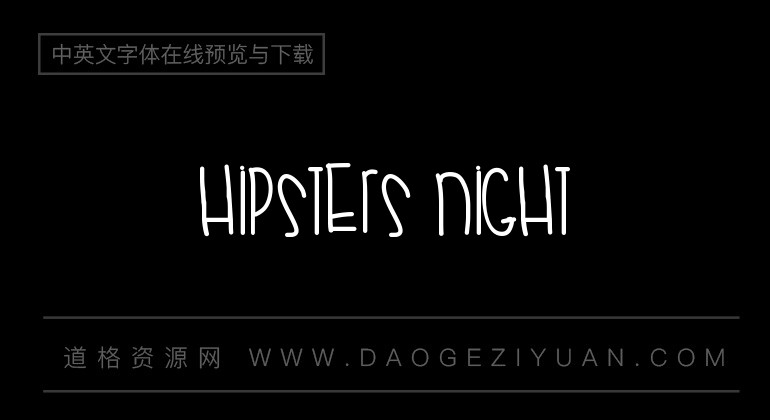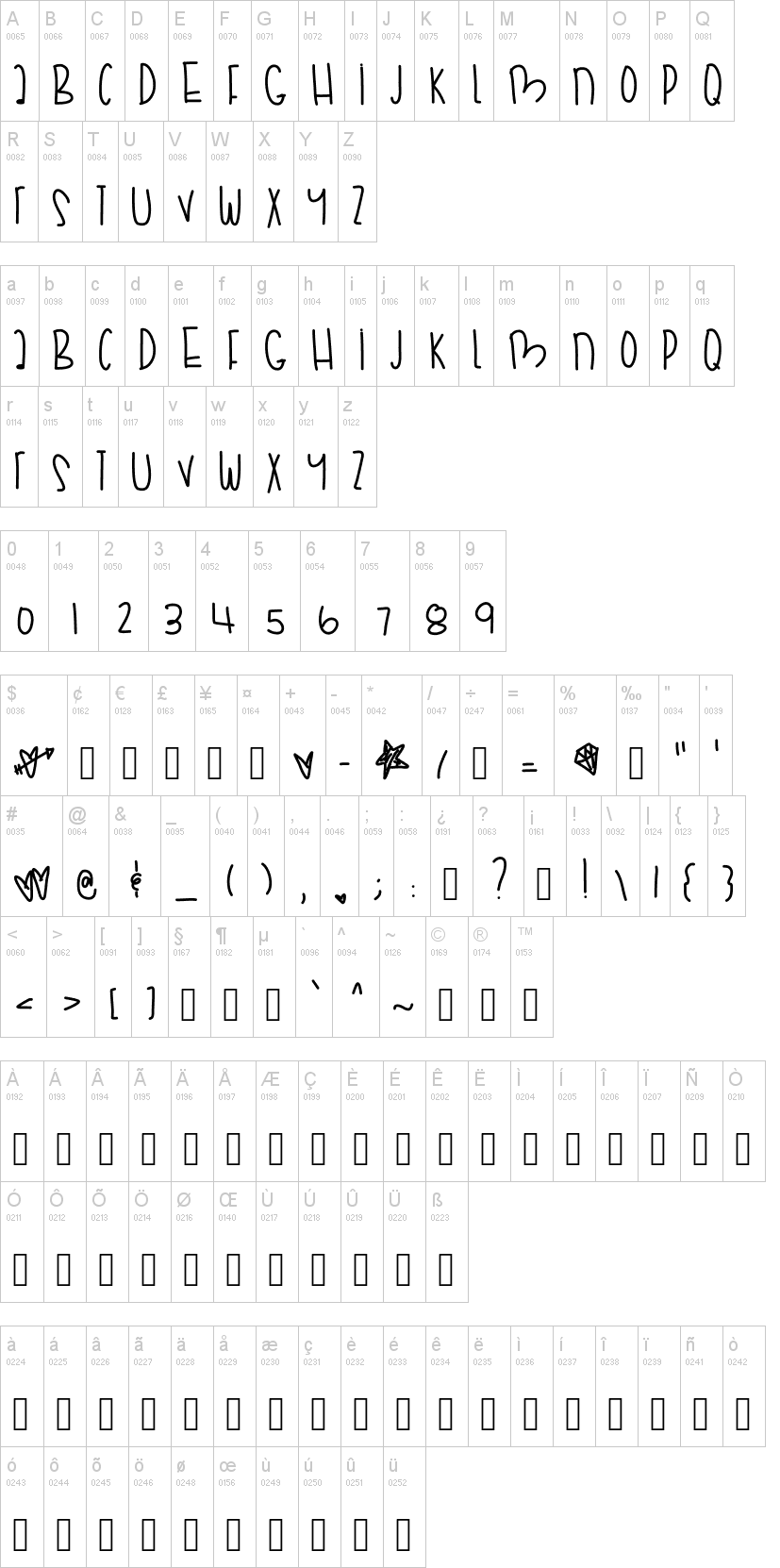
Hipsters Night 是一款由Fontfabric字体工作室设计的手写字体,它具有温柔、活泼、时尚的特点,适合用于海报、书籍封面、品牌标识等设计中。它的字母是用细线绘制的,具有优雅的线条,极具现代感。它的字体样式拥有多种变体,包括常规、斜体、粗体、双倍粗体等,可以满足不同的设计需求。内容介绍
Hipsters Night是一款非常不错的手写艺术字体,具有很好的视觉感,适合于文化类的宣传设计、商业类品牌的广告和产品包装设计以及个性化文字排版等较多场景。